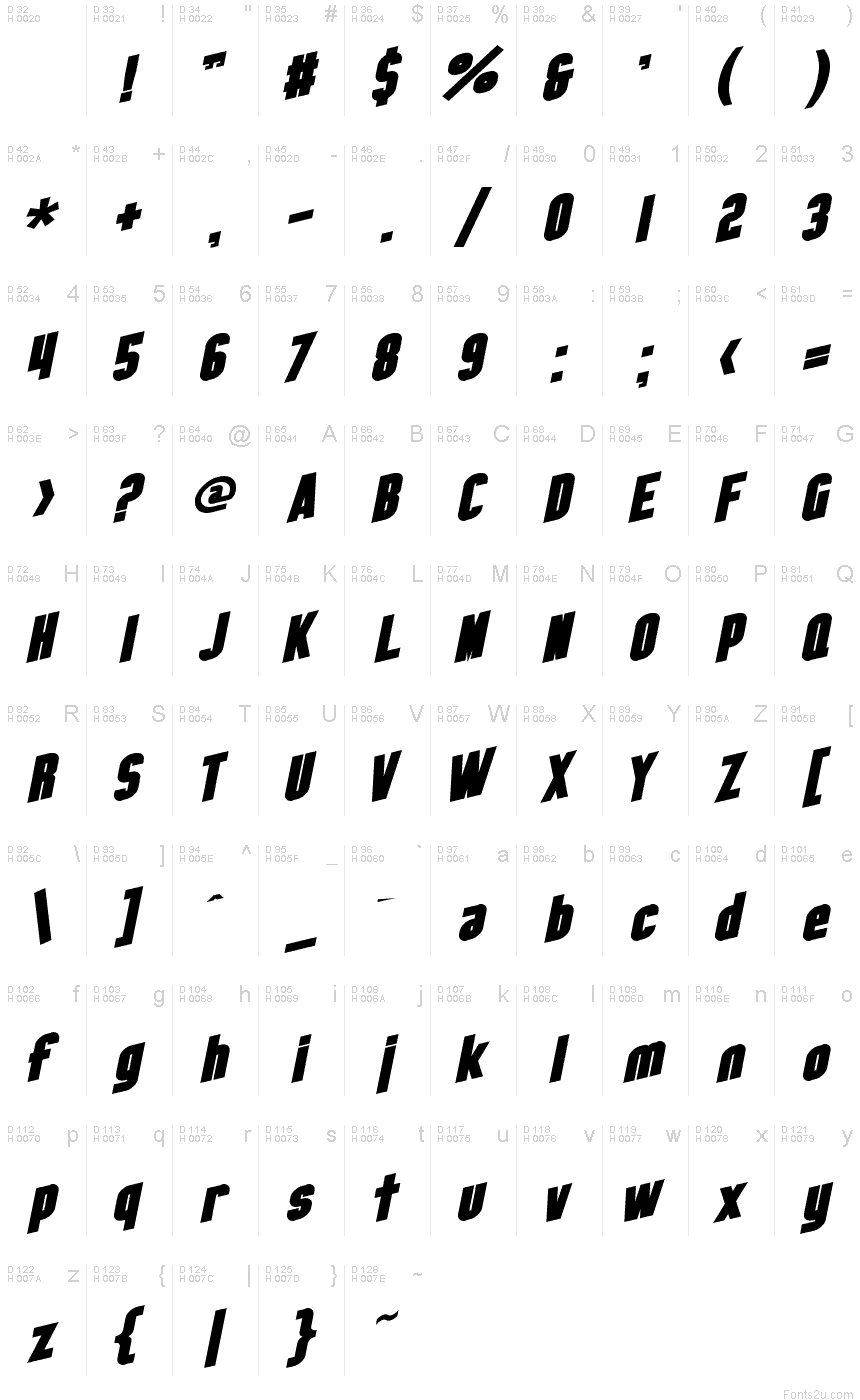
SF Obliquities Bold od ShyFoundry to bezpłatny, pochylony krój typu display o wyrazistym, plakatowym charakterze. Litery są pochylone do przodu, mają szerokie, ciężkie kształty, ostre kąty i ciasne łączenia, co nadaje całości dynamiczny, zwarty i nieco agresywny wygląd.
Świetnie sprawdza się w brandingu sportowym, ulotkach klubowych, tytułach gier, nagłówkach magazynów i odważnych szyldach, gdzie ruch liczy się bardziej niż elegancja. Jako darmowy font, najlepiej wypada w dużych nagłówkach, kartach tytułowych i logotypach, ponieważ gęste nachylenie i ostre cięcia nadają nawet krótkim słowom silny, kierunkowy impet.
SF Obliquities